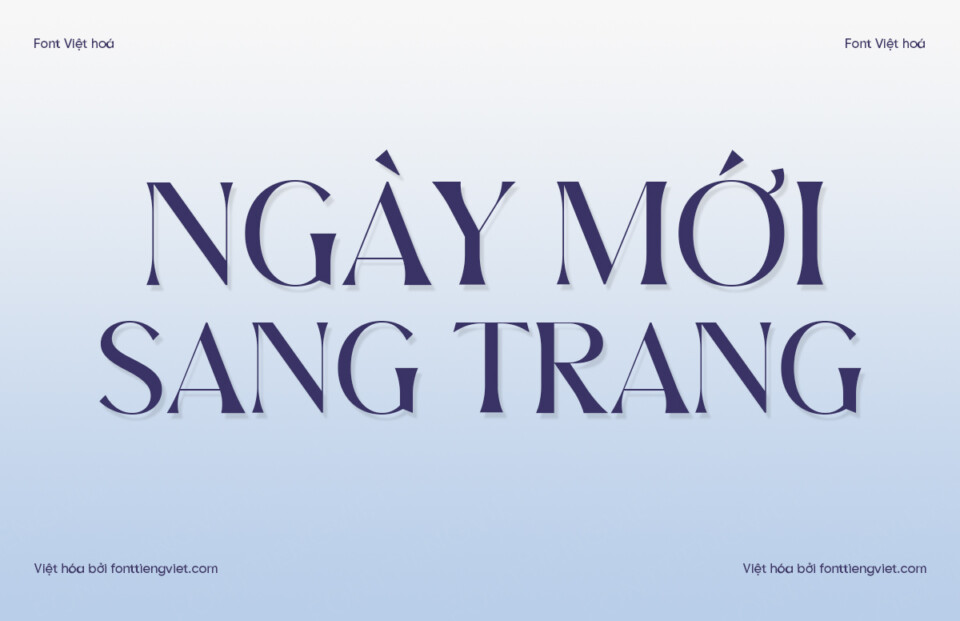
Font Việt hóa 1FTV VIP Brown Volky
Giới thiệu về Font Việt hóa 1FTV VIP Brown Volky
Trong thế giới đồ họa hiện đại, việc lựa chọn bộ Font Miễn Phí chất lượng luôn là ưu tiên hàng đầu của các nhà thiết kế. Đặc biệt, bộ Font Việt hóa 1FTV VIP Brown Volky đã nhanh chóng trở thành tâm điểm chú ý nhờ phong cách độc đáo và tính ứng dụng cao. Đây là một phông chữ thuộc dòng Serif mang hơi hướng cổ điển nhưng không kém phần sang trọng, giúp các tác phẩm thiết kế trở nên nổi bật và chuyên nghiệp hơn. Với việc được Việt hóa chỉn chu bởi đội ngũ 1FTV, người dùng tại Việt Nam giờ đây có thể sử dụng đầy đủ các ký tự tiếng Việt có dấu mà không lo lỗi font hay mất đi vẻ đẹp nguyên bản của chữ cái.
Đặc điểm nổi bật của Font Việt hóa 1FTV VIP Brown Volky
Thiết kế tinh tế và đẳng cấp
Điểm thu hút nhất của Font Việt hóa 1FTV VIP Brown Volky chính là những đường nét uốn lượn mềm mại kết hợp với chân chữ chắc chắn. Sự cân bằng giữa nét thanh và nét đậm tạo nên một cảm giác hài hòa cho thị giác, giúp văn bản dễ đọc hơn dù ở kích thước lớn hay nhỏ. Phông chữ này gợi nhắc đến những bìa tạp chí thời trang danh tiếng hoặc các nhãn hiệu nước hoa cao cấp. Chính vì vậy, nó rất phù hợp cho các dự án thiết kế logo, nhận diện thương hiệu hoặc dàn trang layout sách báo cần sự thanh lịch.
Khả năng tương thích và tối ưu hóa
Khi sử dụng Font Việt hóa 1FTV VIP Brown Volky, bạn sẽ nhận thấy bộ ký tự được chăm chút rất kỹ lưỡng. Các dấu câu tiếng Việt được đặt ở vị trí hợp lý, đảm bảo không bị chồng chéo lên các ký tự xung quanh. Điều này cực kỳ quan trọng đối với các bạn học sinh và giáo viên khi soạn thảo giáo án điện tử hoặc bài thuyết trình. Ngoài ra, font chữ này còn hỗ trợ tốt trên nhiều phần mềm thiết kế chuyên nghiệp như Adobe Photoshop, Illustrator hay cả các ứng dụng văn phòng cơ bản như Microsoft Word và PowerPoint, giúp quy trình làm việc trở nên suôn sẻ hơn bao giờ hết.
Ứng dụng thực tế của Font Việt hóa 1FTV VIP Brown Volky
Thiết kế in ấn và thiệp mời
Nếu bạn đang tìm kiếm một bộ font cho thiệp cưới, thiệp mời sự kiện hoặc menu nhà hàng, Font Việt hóa 1FTV VIP Brown Volky là sự lựa chọn không thể bỏ qua. Vẻ ngoài sang trọng của nó giúp nâng tầm giá trị cho các ấn phẩm in ấn. Bạn có thể kết hợp phông chữ này với các tông màu trung tính như vàng đồng, nâu đất hoặc trắng kem để tạo ra hiệu ứng thẩm mỹ tốt nhất. Sự tỉ mỉ trong từng đường nét sẽ giúp thông điệp của bạn chạm đến cảm xúc của người nhận một cách tinh tế nhất.
Truyền thông mạng xã hội
Trong thời đại nội dung số, các bài đăng trên Facebook, Instagram hay Canva cần có hình ảnh bắt mắt để thu hút người xem. Sử dụng Font Việt hóa 1FTV VIP Brown Volky cho các câu trích dẫn (quotes) hoặc tiêu đề ảnh bìa sẽ giúp trang cá nhân của bạn trở nên nghệ thuật hơn. Với phong cách VIP độc quyền, bộ font này giúp tạo ra sự khác biệt so với những phông chữ phổ thông tràn lan hiện nay. Đừng ngần ngại trải nghiệm để khám phá sức mạnh truyền tải thông tin của nó.
Kết luận về bộ phông chữ 1FTV VIP Brown Volky